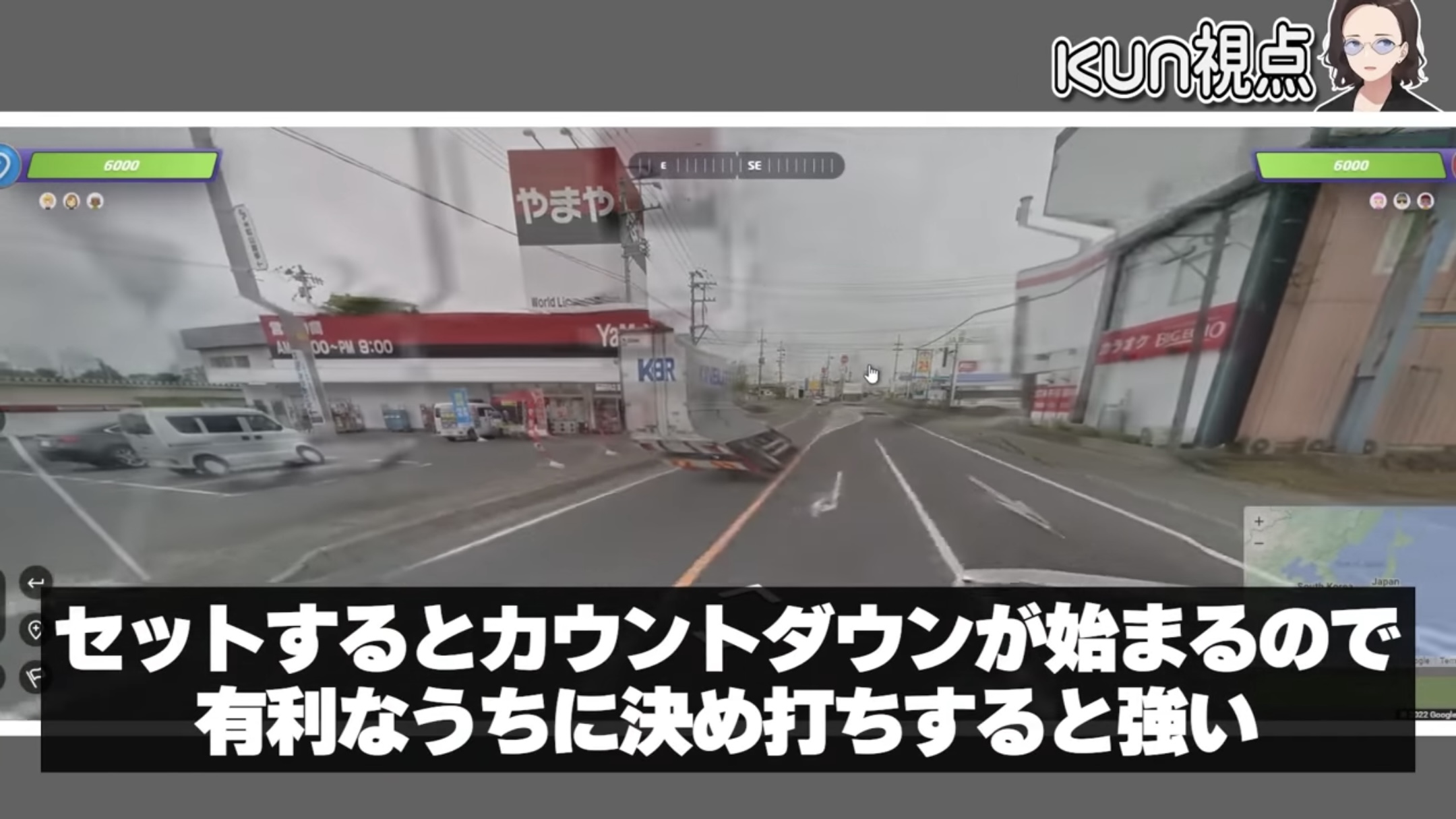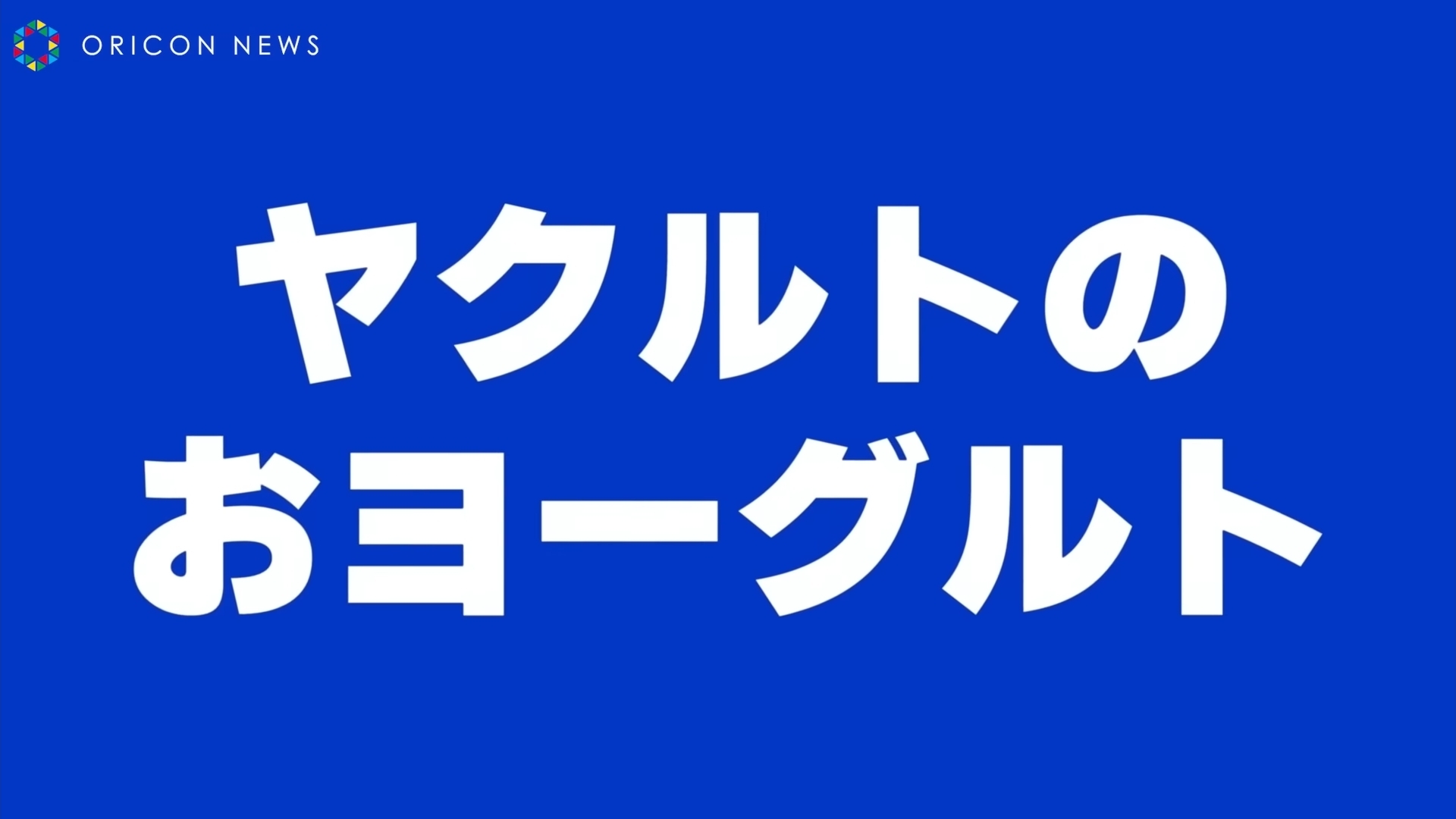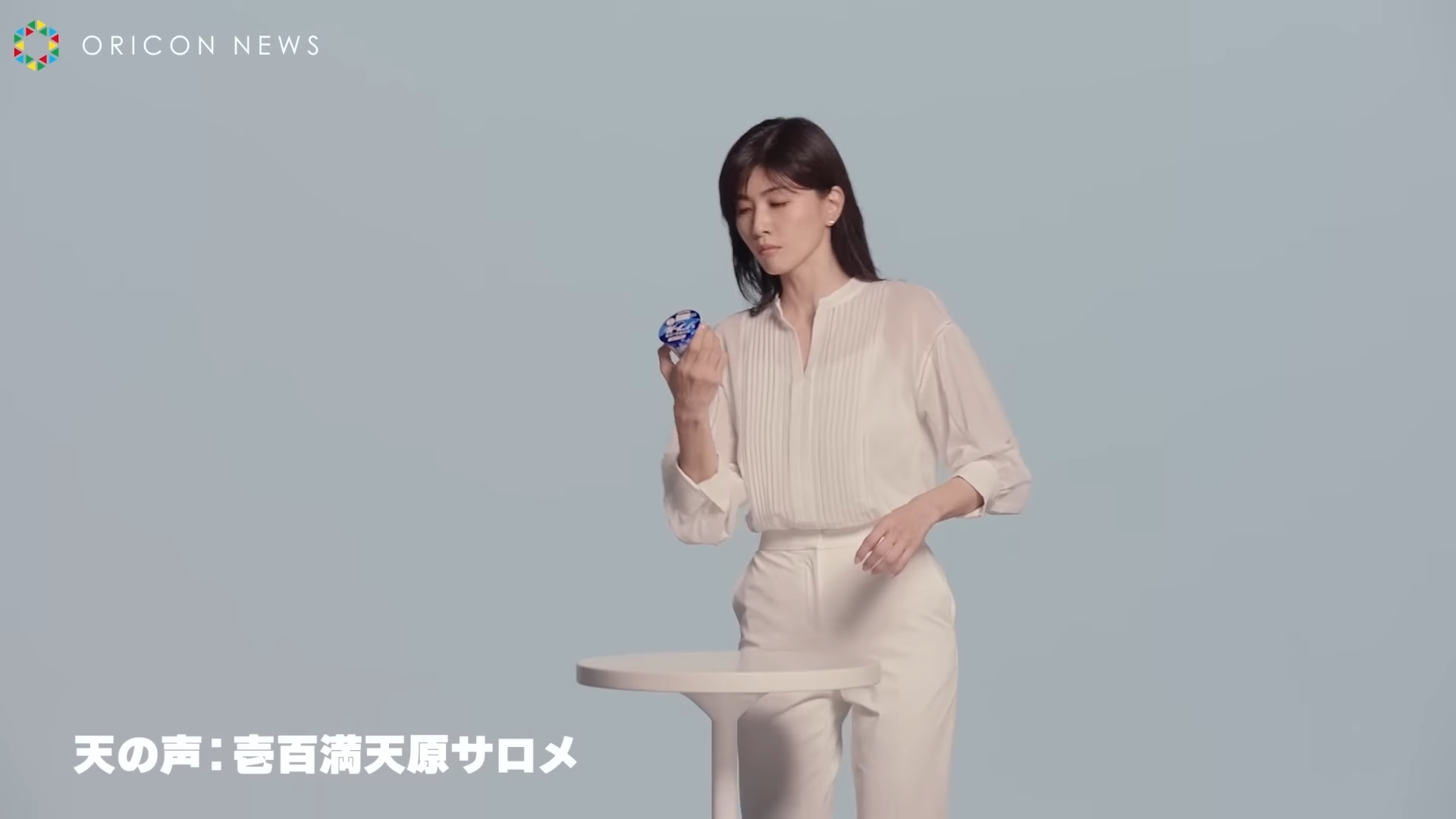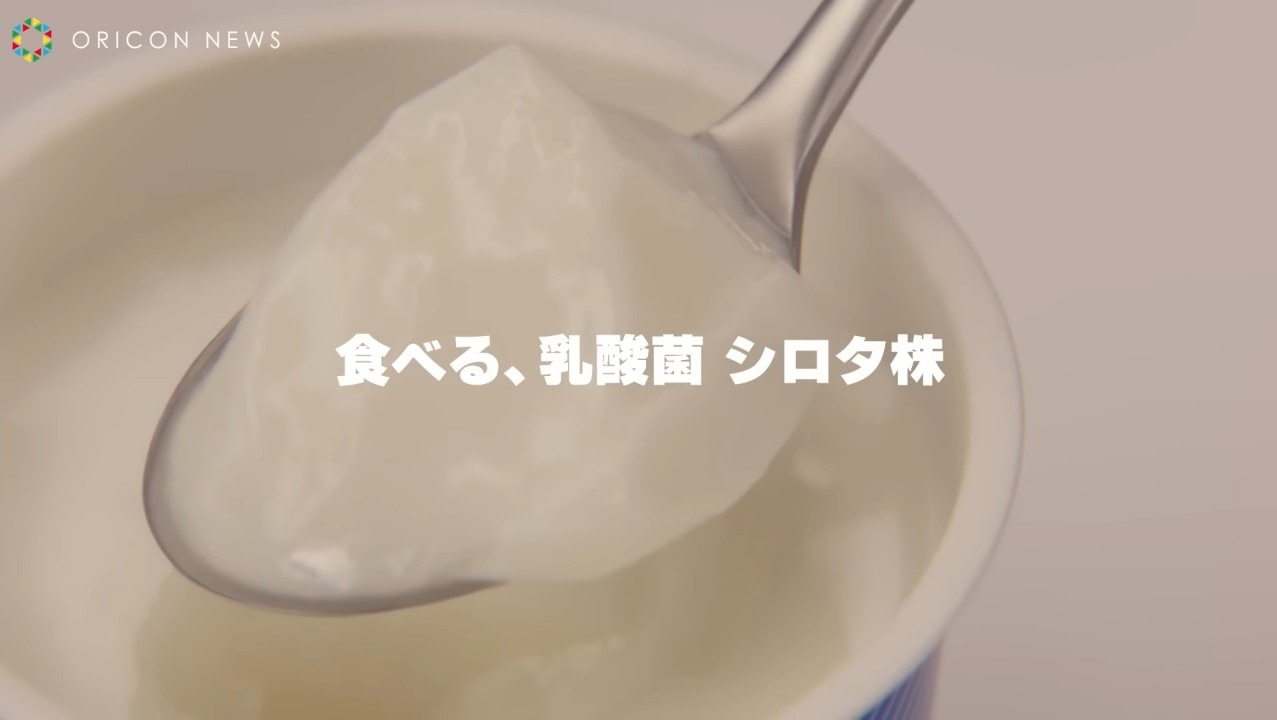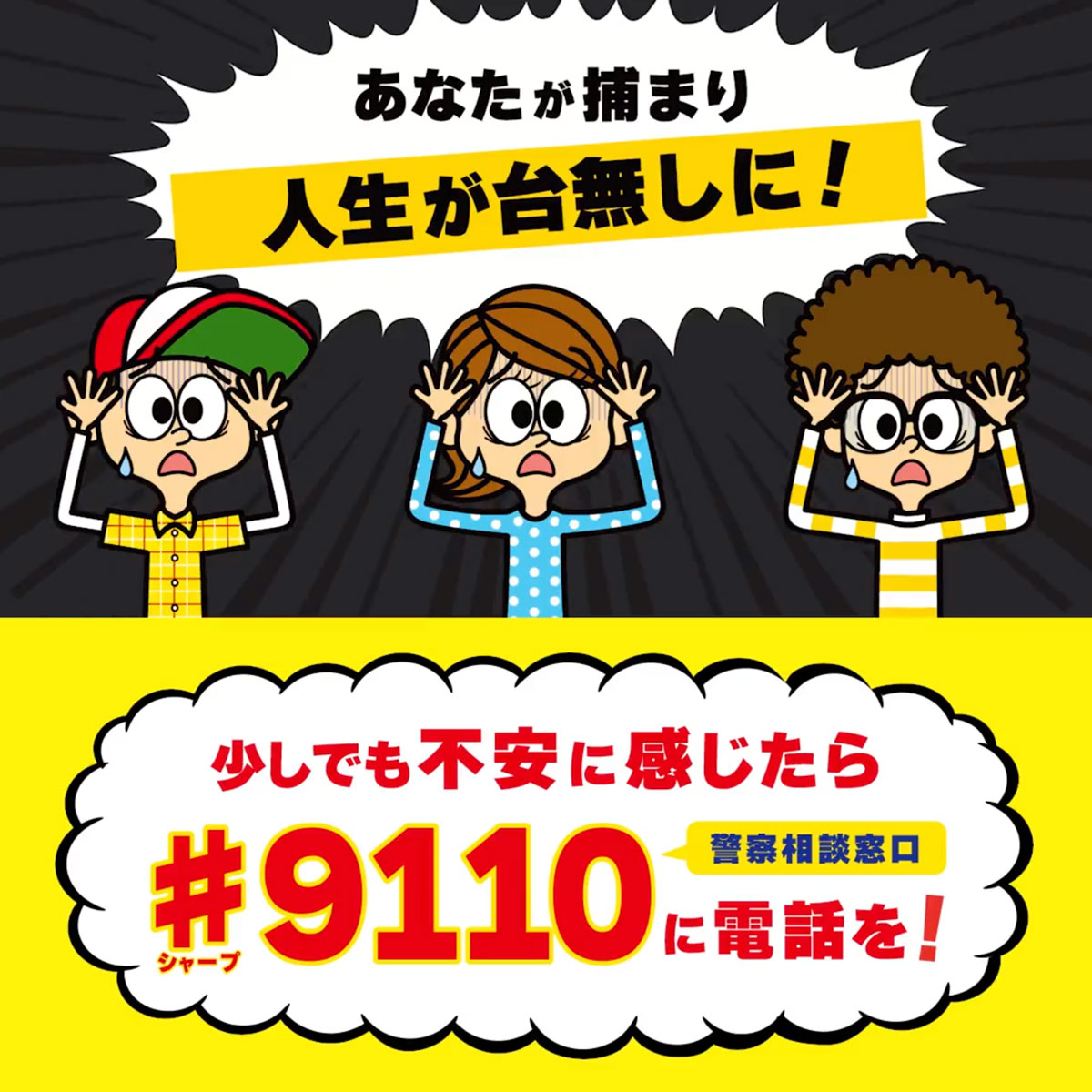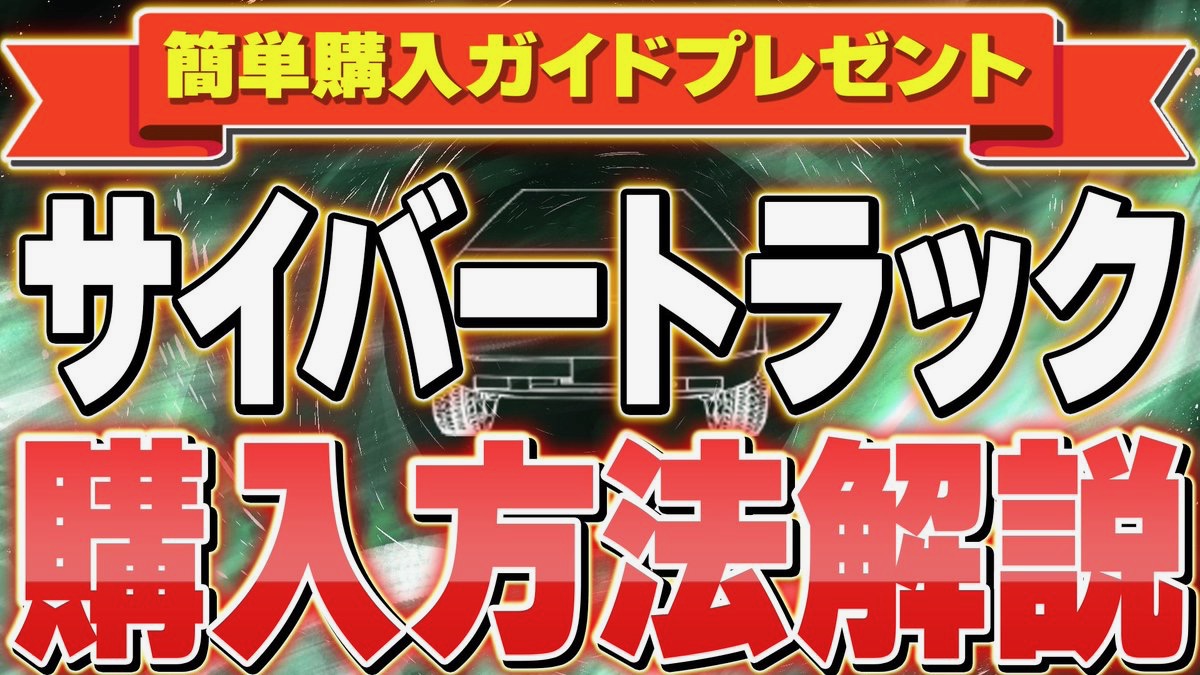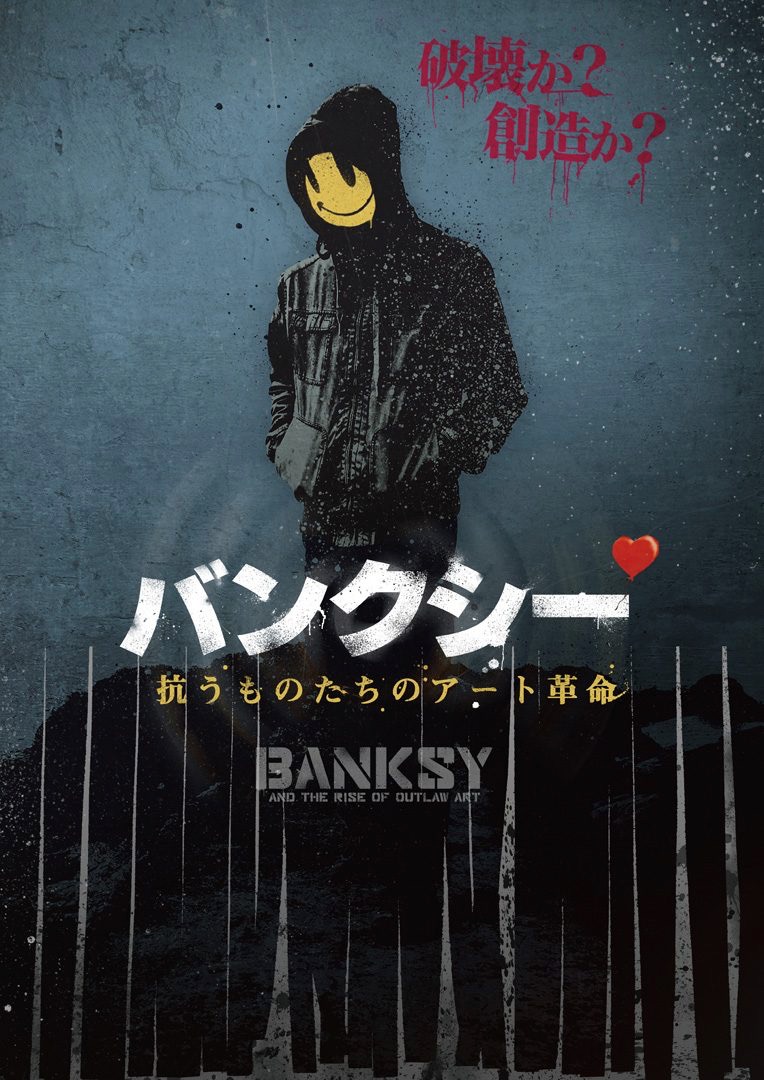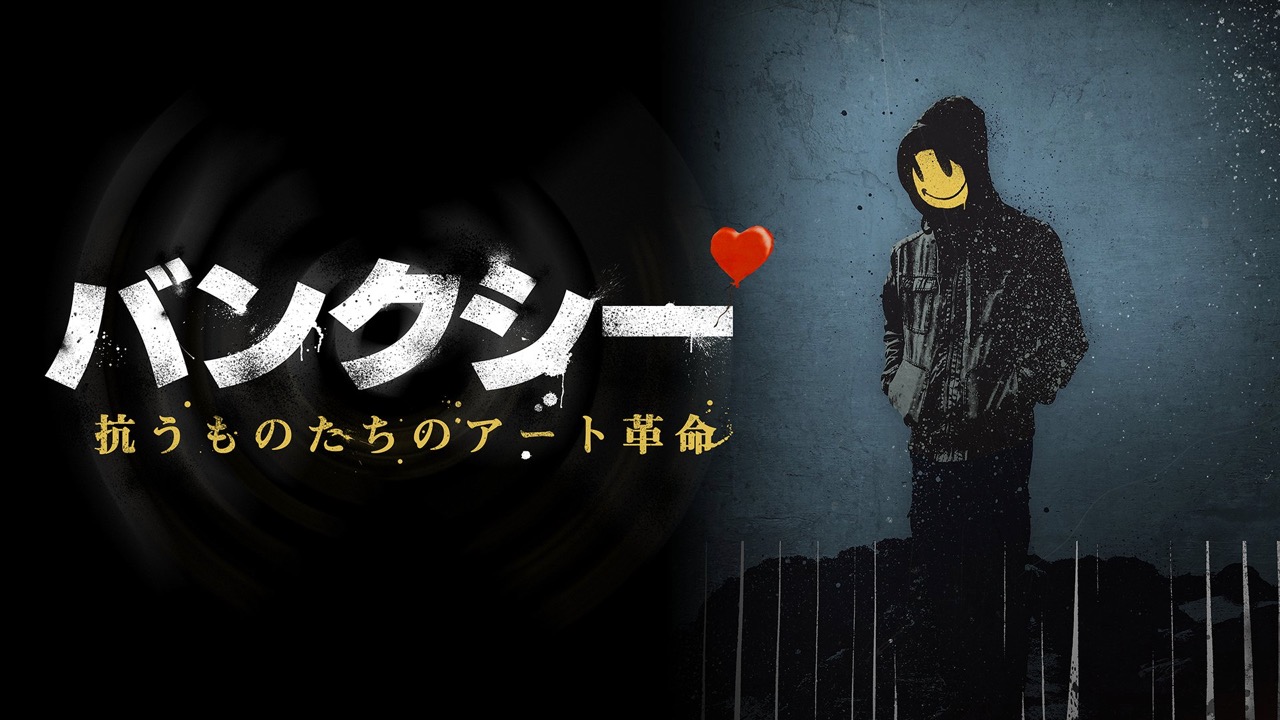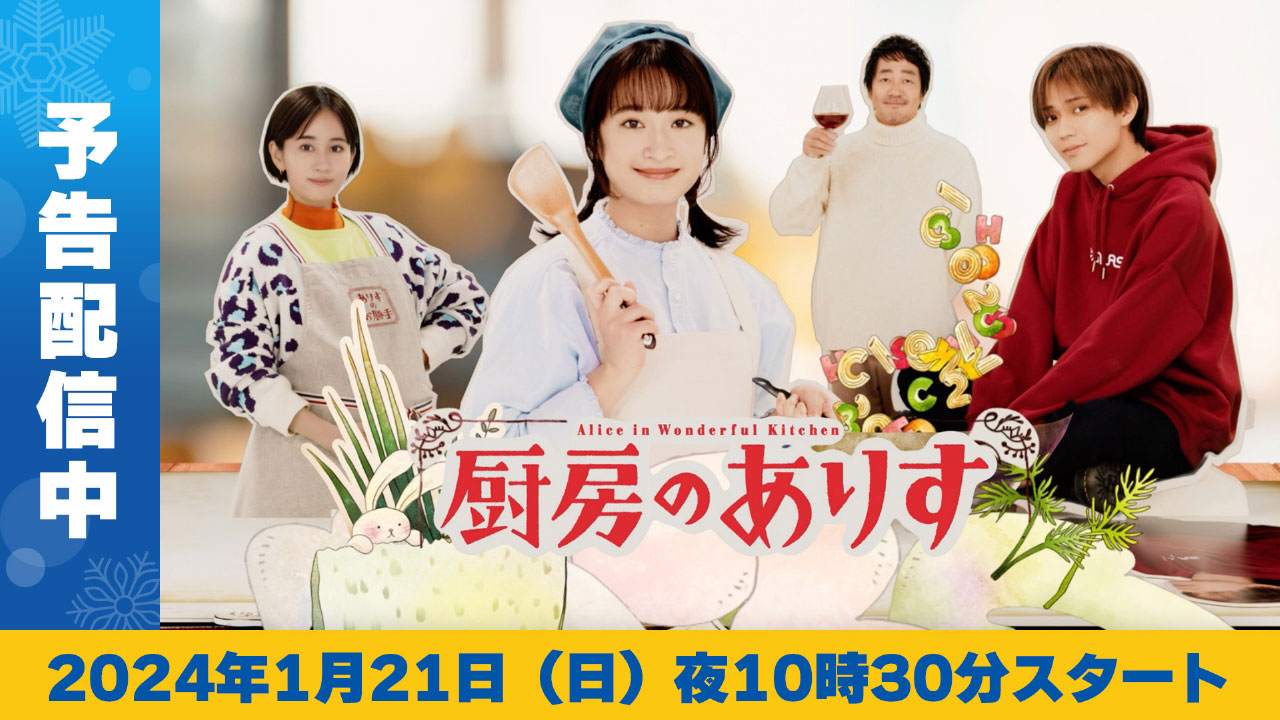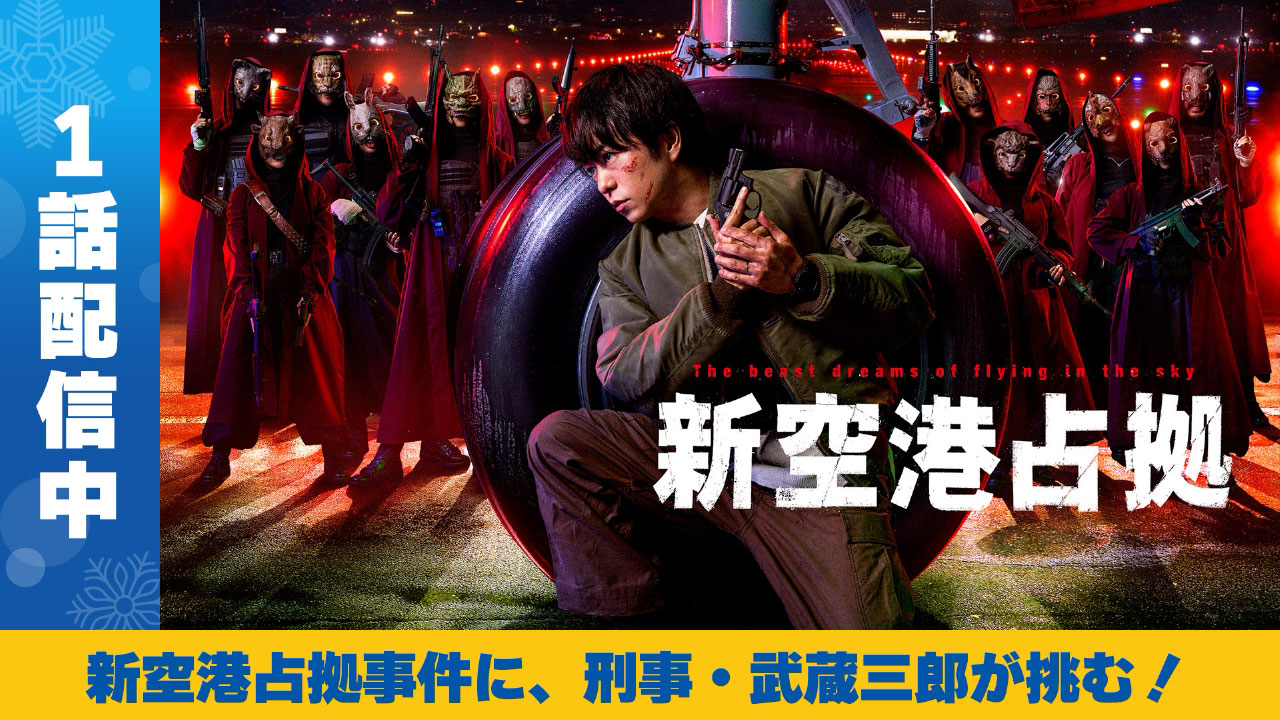
世界卓球2026ロンドン100周年大会 (団体戦)5月2日(土)開幕!
もうひとつ。
金色のバージョンも。
この動画の中では、ルイカは紹介されていない…残念!
映画館で見かけたやつ。
ルイカ書体は、クセのない普通の表情でありながら、強く訴える力も持っている…。
一部にはニタラゴルイカも使われている。
ルイカ書体の一番太いウェイト。
ごく普通の表情でありながら、強く訴える力も持っているフォントだ。
アニメ「タコピーの原罪」公式サイト内での「ルイカ」使用例です。
もう1枚。
ルイカがたくさん使われてますね〜。
同アニメの公式Xで投稿されている画像でもルイカが使われているようですので追加で載せておきます。
同じく公式Xよりもう1枚。
「スーパーマリオ フルーツサマーソルベ」篇。
使われているのは、ルイカ書体の一番太いウェイト。
7月2日まで行われている「スクウェア・エニックス アルティメットセール ~JUNE 2025 Part3~」の広告媒体。
「JUNE 2025」とか、「Part3 7/2まで」の文字がルイカですね。
漢字と英字の大きさが違和感なく、気持ち良い。
タイプラボ書体の特徴だな。
もうひとつ。
相変わらず、Youtuberに人気があるようだ。